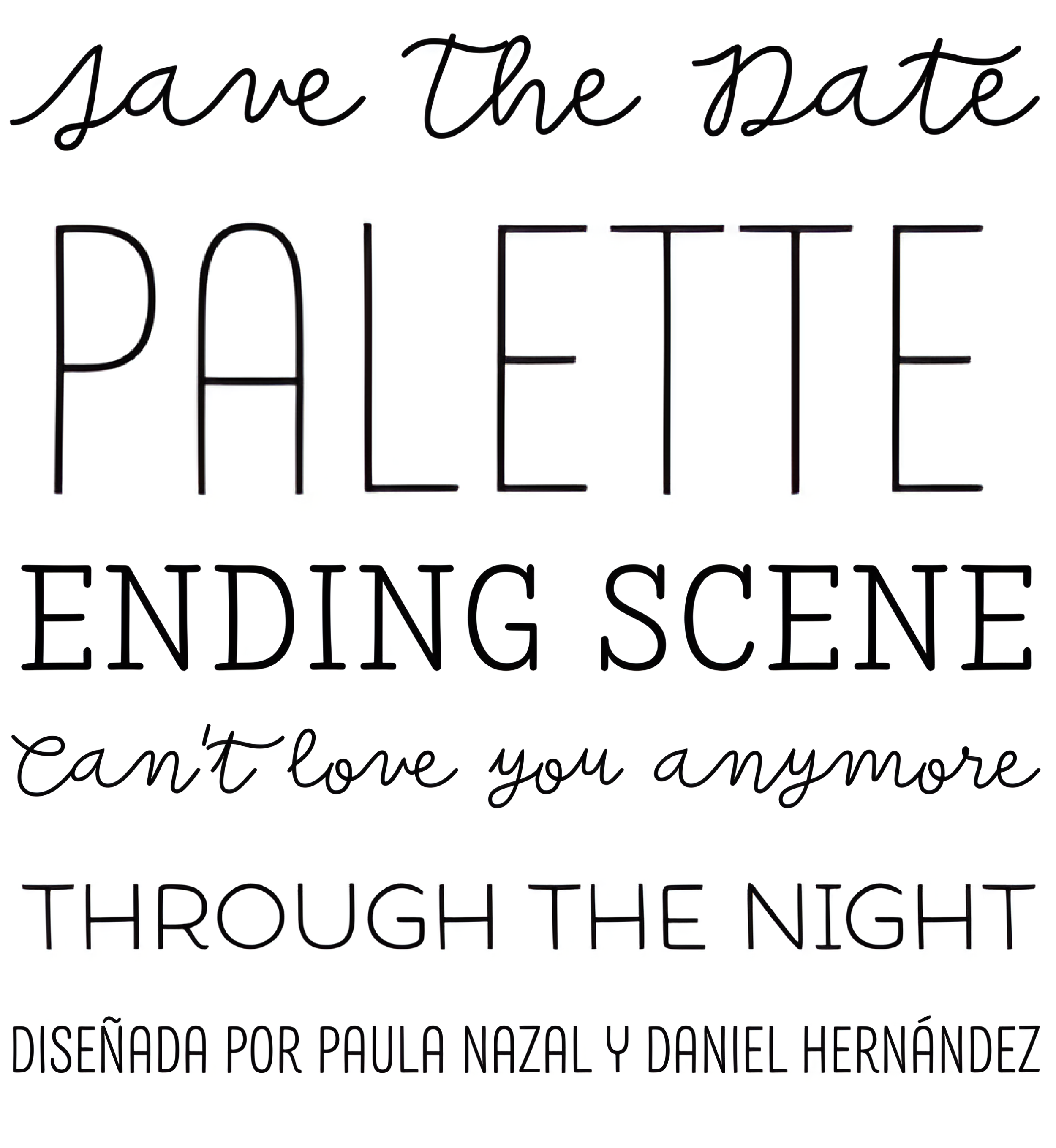
| Descripción | Una boda empieza mucho antes del «sí, quiero» del gran día: todos colaboran a lo largo del proceso para que todo salga según lo previsto: los detalles, las combinaciones de colores, la decoración, la forma en que transmitimos la magia de los elementos visuales y transmitimos nuestro mensaje de amor. A través de esta hermosa tipografía, nos gustaría transmitirte ese mismo mensaje, que lo hagas tuyo y te expreses a tu manera a través de la invitación perfecta el día de tu boda. No importa lo dulce o salvaje que parezca tu invitación, intenta ser tú mismo. Save the Date es una colección de fuentes que consta de 9 estilos y 4 variantes: Script, Sans, Serif y Small. El conjunto de fuentes está pensado para ofrecer a los usuarios una amplia gama de opciones para cualquier proyecto de diseño. Save the Date ha sido diseñado por Paula Nazal y Daniel Hernández. Edición digital de Rodrigo Fuenzalida. Fotos de Mónica Muñoz. Mónica se especializa en fotografía de bodas. |
| Familia(s) | Save the date |